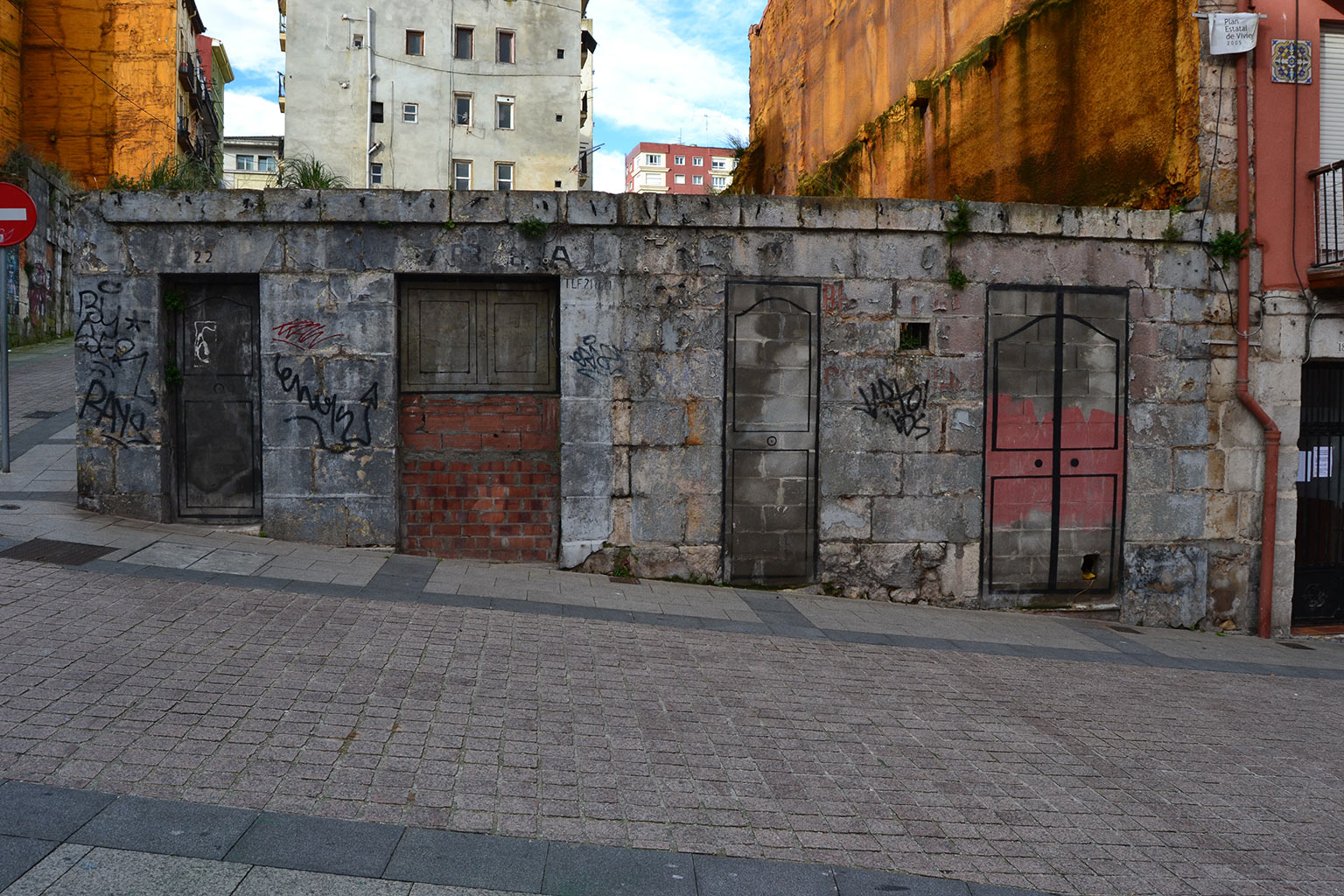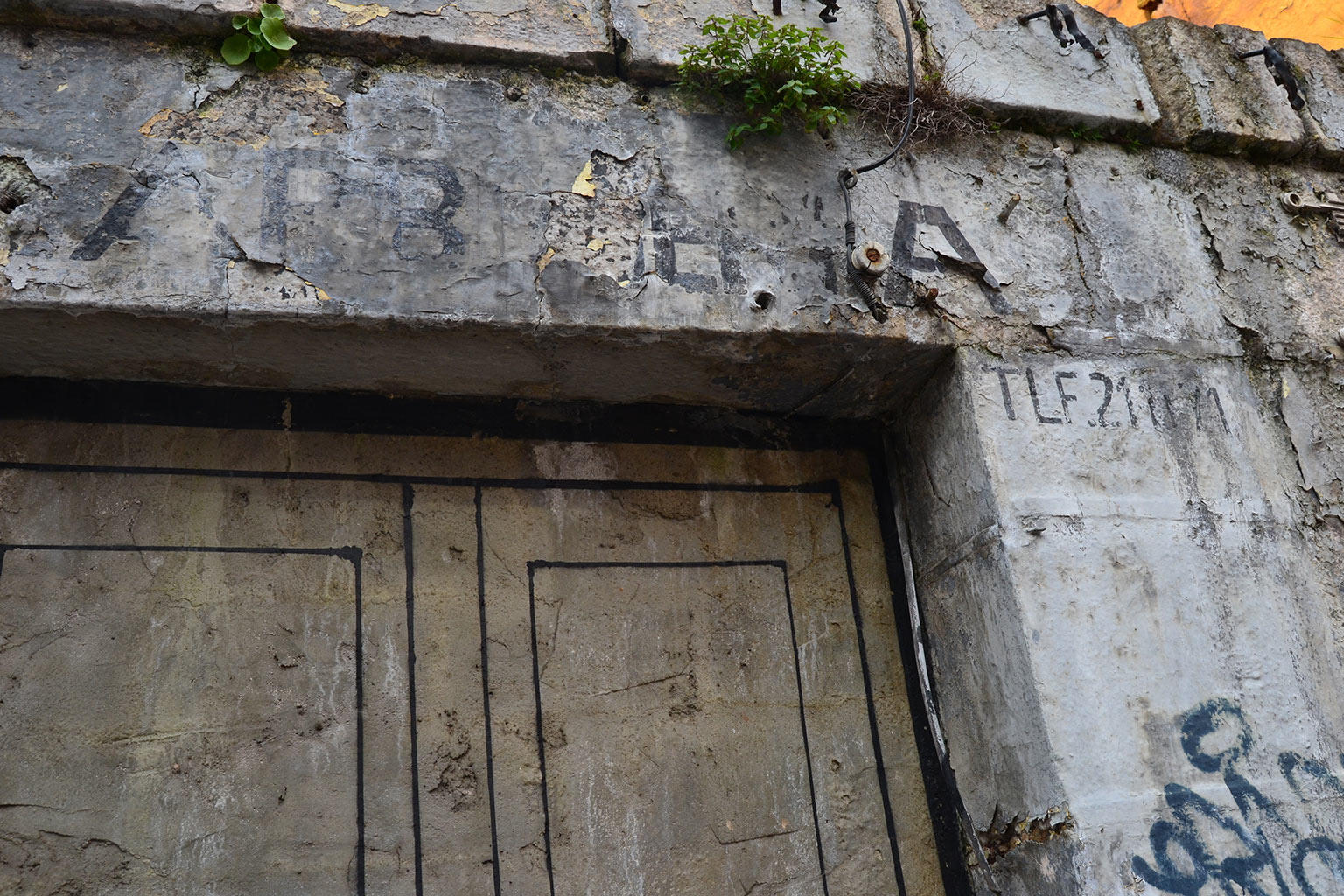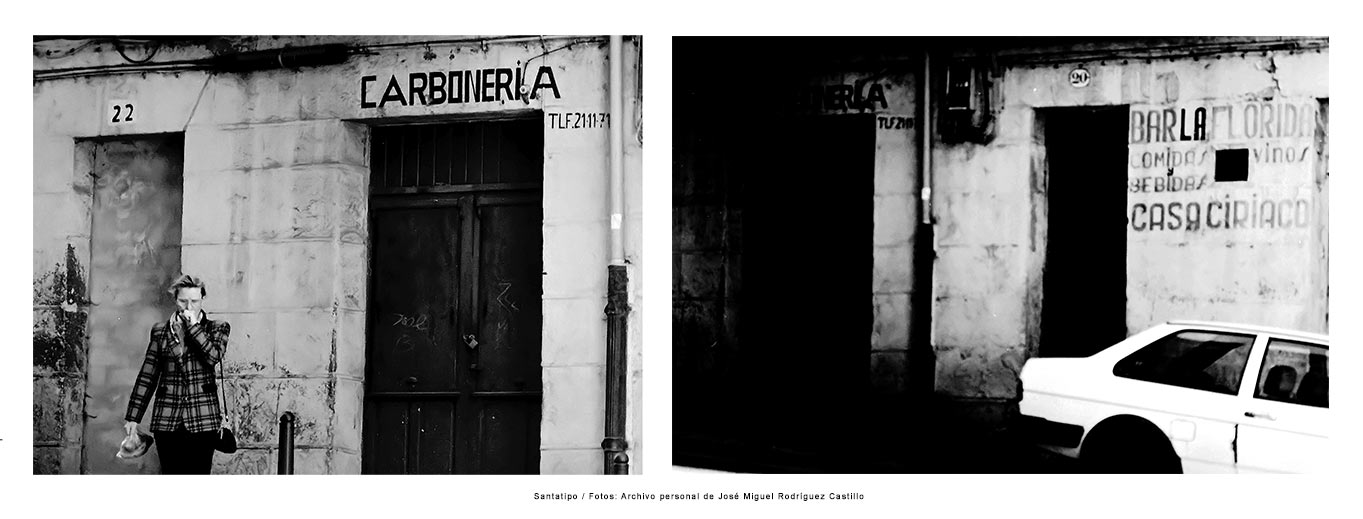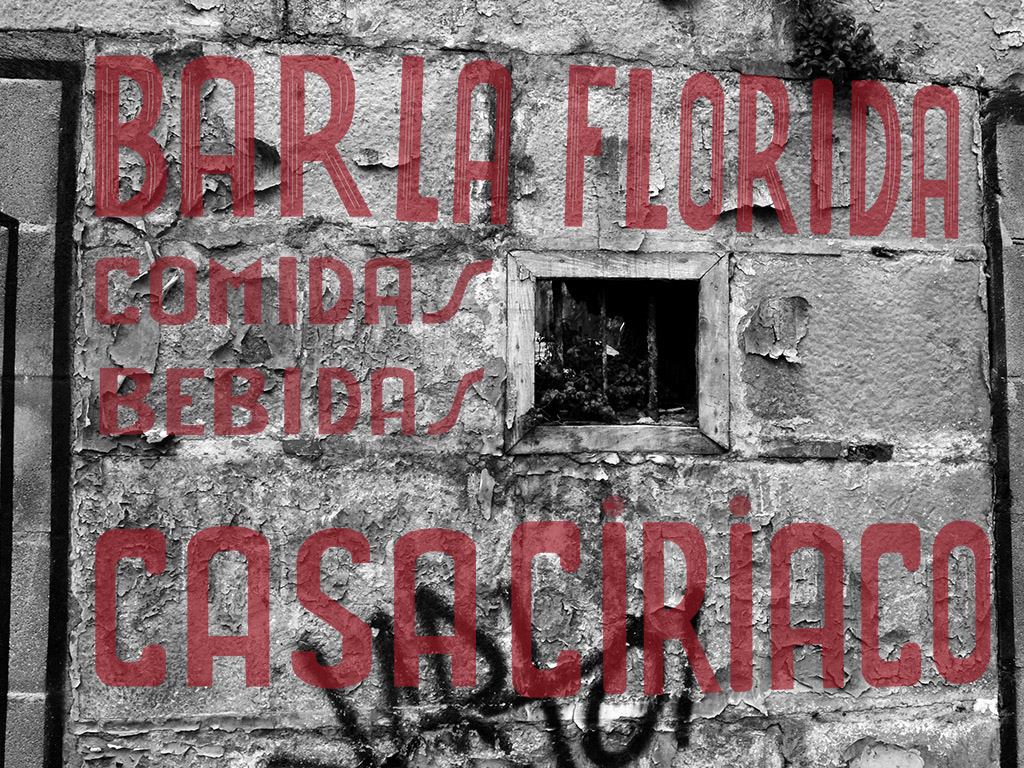
Bar La Florida – Casa Ciriaco
En el Cabildo de Arriba (Santander) aún quedan vestigios del barrio que fue, pero que poco a poco va desapareciendo. Una de esas fachadas, sita en la Cuesta del Hospital, guardaba en sus paredes un pequeño secreto.
Detrás de este grafiti había restos gráficos de dos negocios del barrio:
Una CARBONERIA de entorno a los años 50-60, pero que estuvo activa hasta finales de los 70, siendo probablemente la última en activo, y que según algún vecino aún recordaba como de niño veía llegar y salir Burros con carbón para repartir por la ciudad, en la que se leía sobre el dintel  de la puerta izquierda «Carbonería» y anexo un teléfono «211171».
Y a su derecha restos de trazos en tono rojos de unas palabras, que según los mismo vecinos era conocido como BAR CIRIACO.
Esto ha sido visible desde su apertura hasta 2019, cuando todo fue cubierto por el graffiti de arriba. Pero, eso no quitó que la casualidad hiciese revivir estos trazo. Durante el trabajo de edición del libro «Santatipo», llegaron unas fotos que dieron luz a estas letras.
Con estos datos, se ha podido reconstruir de nuevo lo que en su dia fue un bar de barrio, muy de parroquia como bien nos decía un vecino. Letras pintadas a mano sobre pared, en tono rojo, con una serie de rayas decorativas. Parte que ya ha desaparecido para siempre, pero que vuelve al presente para siempre, como un recuerdo permanente.